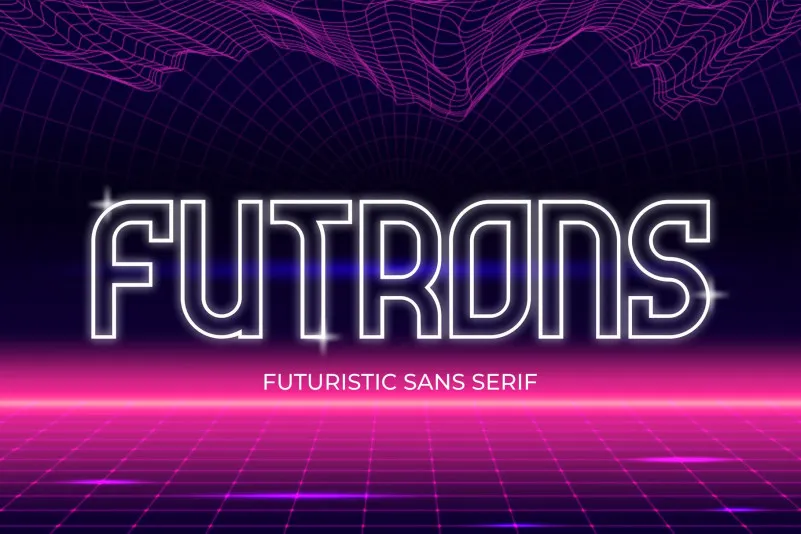
Futrons Font
A Futrons Font é uma elegante fonte sans serif criada pela Figuree Studio com um toque contemporâneo ideal para criações visuais. Suas linhas limpas e minimalistas se destacam, tornando-a perfeita para logos e identidades de marca. Além disso, a Futrons apresenta alternativas galáxias que mostram uma design futurista minimalista, um conjunto único em sua categoria. Este conjunto de caracteres pode levar você a aventuras temporais, tanto se aplicar para o título de posters de filmes no espaço ou na era futura. A Futrons é perfeitamente adequada para entusiastas de ficção científica e permite que você crie cartazes e arte personalizada. Seu design também se destaca em projetos UX/UI, oferecendo uma visão para o futuro da interface do usuário e experiência do usuário.